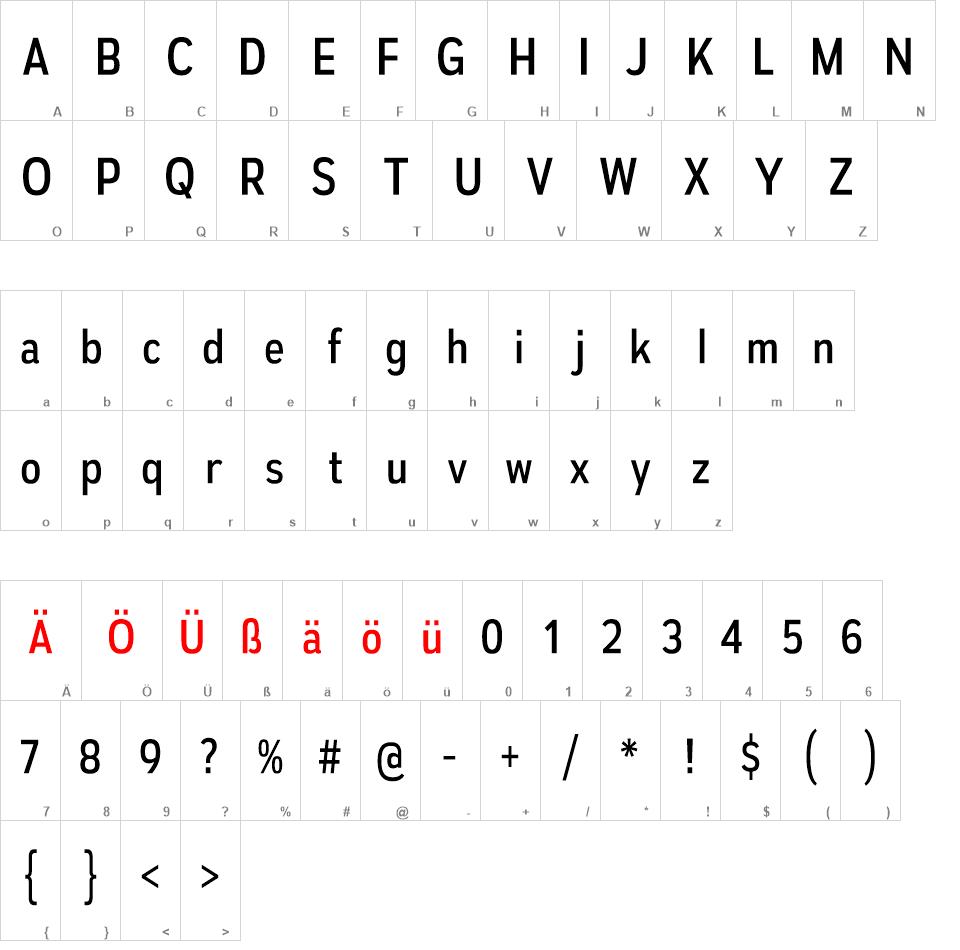
Autoradiographic
Autoradiographic font
Autoradiographic
Autoradiographie ist eine 5-gewichtige serifenlose Schrift, die die handgemalten Warnzeichen in der Mitte des zwanzigsten Jahrhunderts inspirierte. Entzündlich! Halten Sie es raus! Die niedrigen Taillenlinien der Nachkriegszeit waren in diesen Jahren glatt, jedoch nicht an der Taille. Solche informativen Schriften sollten rein und technisch sein, aber etwas Persönlichkeit glänzte. Enthält autoradiographische, kyrillische, mathematische Symbole, Brüche und die neuesten Geldsymbole. Kursive sind in Abständen angeordnet, um den Schwerpunkt auf eng und locker zu legen. Die Desktop-Lizenz für normale und kursive Formate ist kostenlos.